Создай текст в золотой оправе в Фотошоп
В этом простом уроке Вы узнаете, как создать королевский золотой текст, используя стили слоя в Фотошоп. Приступим!
Шаг 1. Создайте новый документ 600Х400 пикселей в режиме RGB и с разрешением 72 DPI любым фоновым цветом. Подготовьте активы урока: установите шрифт Xenippa на компьютер и откройте оба .PAT файла.
Шаг 2. Идем в Меню>Слои>Стиль слоя>Параметры наложения (Menu > Layer > Layer Style > Blending Options), используйте настройки, приведенные ниже. Вы также можете вызвать окошко стилей слоя, дважды кликнув по слою на панели. Еще один способ – кликните правой кнопкой мыши по слою в палитре и выберете со всплывающего меню Параметры наложения (Blending Options). Когда все параметры, приведенные ниже, будут применены, не забудьте нажать «ОК» в окне для сохранения изменений.
Шаг 3. Работу над фоном закончили, теперь приступим к тексту. Сперва возьмите инструмент Текст (Type tool) (T), выберете шрифт Xenippa, установите размер 250 пт и метод сглаживания (anti-aliasing) Резкое (Sharp). Напечатайте ваш текст в центре изображение. Вы можете написать любое слово, в этом уроке я решил напечатать «Lord».
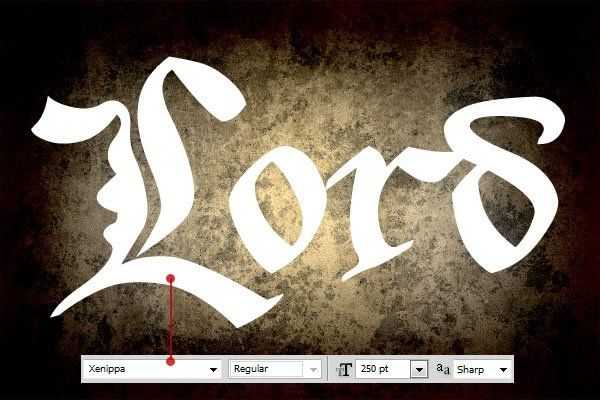
Шаг 4. Теперь разберемся со стилями текстового слоя. Идем в Меню>Слои>Стиль слоя>Параметры наложения (Menu > Layer > Layer Style > Blending Options), используйте настройки, приведенные ниже. Вы можете воспользоваться одним из быстрых вызовов стилей слоя, которые описаны в шаге 2. Когда примените все настройки, нажмите «ОК» для их сохранения.
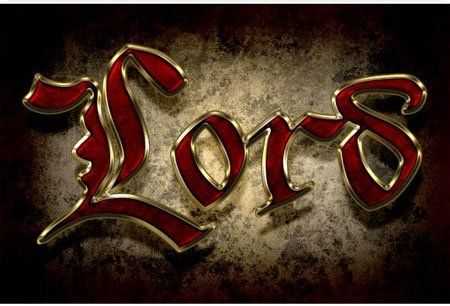
Шаг 4. Мы близки к финалу. Сейчас нам нужно дублировать текстовый слой. Стоя на слое с текстом, идите в Меню>Слои>Дублировать слой (Menu > Layer > Duplicate layer), назовите его как пожелаете. Теперь идем в Меню>Слой>Стиль слоя>Очистить стили слоя (Menu > Layer > Layer Style > Clear Layer Style), ведь для этого слоя мы будем использовать другие стили.
Опять идем в Меню>Слой>Стиль слоя>Параметры наложения (Menu > Layer > Layer Style > Blending Options), используем настройки, приведенные ниже. Или вы можете использовать быстрые методы вызова окна стилей, которые описаны в шаге 2. Не забудьте нажать «ОК», когда примените все настройки.
Вы успешно выполнили урок. Текст должен выглядеть так, как на изображении ниже.
Автор: Jan Stverak
Создаём в Фотошоп яркий золотой текст
В этом небольшом уроке вы узнаете, как создать золотой мультяшный текстовой эффект, используя стили слоя в Фотошоп. Давайте начнем!
Сначала создайте новый .PSD документ, 600 х 400 пикселей в RGB режиме, 72 точек на дюйм с белым фоном. Теперь подготовим наши материалы. Установите шрифт HVD Comic Serif на ваш компьютер и откройте .PAT файлы.
Перейдите в Menu> Layer> Layer Style> Blending Options (Меню>Слой>Стиль слоя>Параметры наложения) и используйте настройки ниже. Вы также можете получить доступ к Параметрам наложения двумя более быстрыми способами. Первый и самый быстрый способ это дважды щелкнуть на слое в меню слоев. Другой способ: Нажмите правой кнопкой мыши на слое в меню слоев и выберите Режимы наложения. Когда вы закончите со всеми настройками ниже, не забудьте нажать «OK» в окне настроек наложения!
Внутреннее свечение: Режим наложения: Линейный затемнитель, непрозрачность 44%, шум 4%, цвет #172320, метод-мягкий, источник-в центре, стягивание 0%, размер 147 пикс., диапазон 68%, колебание 0%.
Наложение градиента: Режим наложения — Умножение, непрозрачность 80%, градиент от #014806 до #bee96b, стиль-линейный, галочка «выровнять по слою», угол 132, масштаб 100%.
Следующий шаг в Параметрах наложения – это Наложение узора с настройками, как показано на рисунках ниже. После того, как вы используете текстуру «whirl» , вы увидите, что она расположена не в центре фона. Возьмите текстуру на вашем рисунке с помощью мыши, пока вы еще находитесь в настройках наложения, переместите её в центр.
Наложение узора: Режим наложения — Умножение, непрозрачность 12%, используйте текстуру «Whirl», масштаб 100%.
Хорошо, объедините все слои в один, кроме фона и примените стили слоя (тень, внешнее свечение), как показано на картинках:
И последняя вещь, которую мы должны добавить, блик. Для этого эффекта создайте новый слой и залейте его черным цветом. Затем измените режим слоя на осветление (screen) и примените Filter> Render> Lens Flare (фильтр> рендеринг> блик) с такими настройками:
Мы получим следующий эффект: